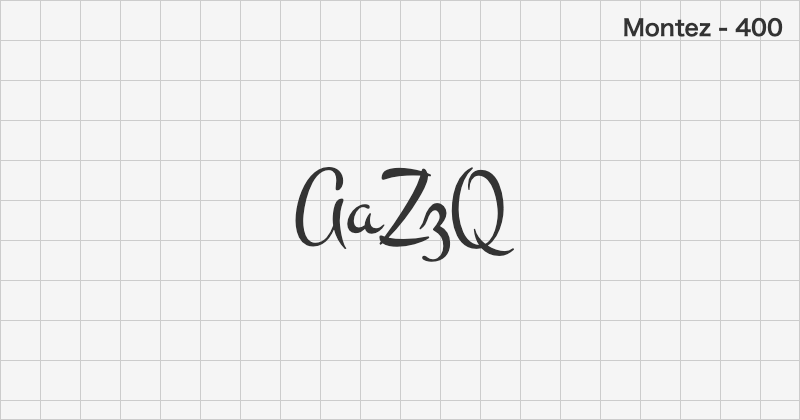
Montez – 商用利用できる手書きフリーフォント
Montez は、1960年代の美容製品広告からインスパイアされた筆記体フォントです。流れるようなストロークが、喜びとエレガンスを表現します。
Montez は、アメリカ・シカゴを拠点とするタイプファウンドリー Astigmatic によって手がけられ、視覚的なインパクトを持つデザインを目指しています。